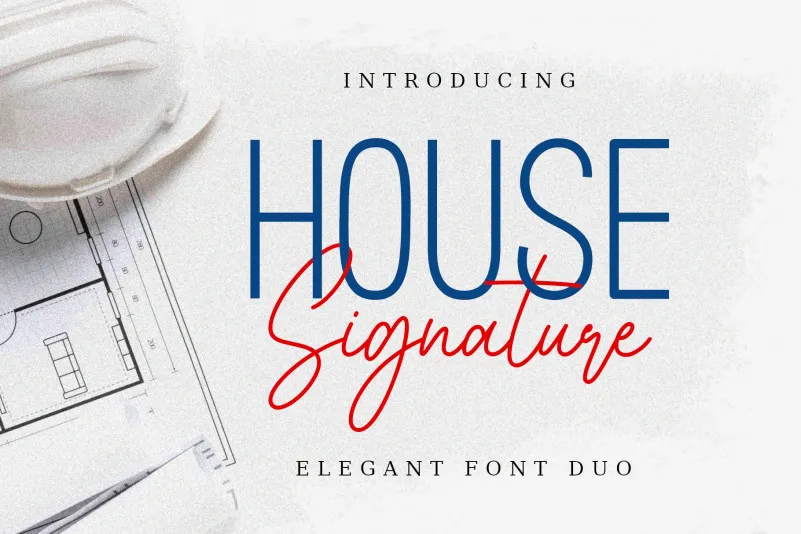
House Signature Font Duo – Download Grátis
A House Signature Font Duo é uma nova combinação de fontes serifadas manuscritas que oferece alternativas incríveis para seus projetos digitais criativos. Foi desenvolvida pela equipe de designer AV Type, conhecida por criar lindas e únicas fontes sem serif. Esta fonte não apenas destaca-se por sua elegância e sofisticação, mas também é extremamente versátil para uma ampla gama de aplicações gráficas. Perfeita tanto para projetos como posters e logomarcas quanto para capas de livros e cartões de visita, esta fonte pode ser facilmente incorporada em diversos tipos de material impresso e impressão digital. Aproveite sua versatilidade e personalize suas criações com o estilo único da House Signature Font Duo, disponível agora para download.